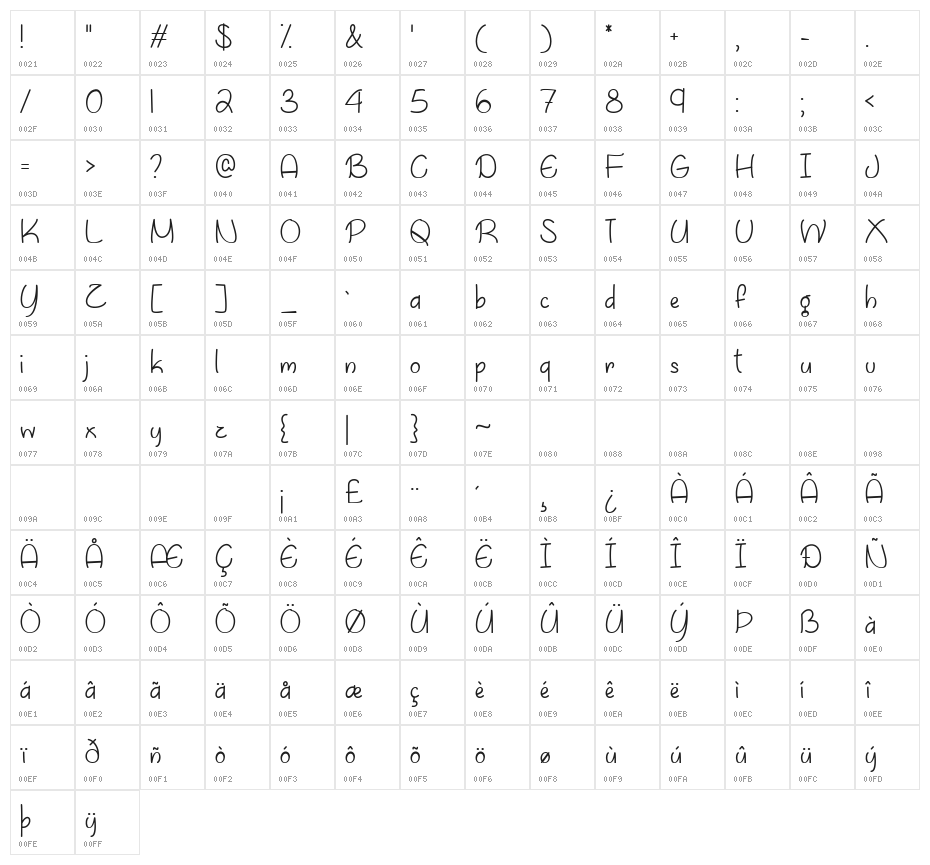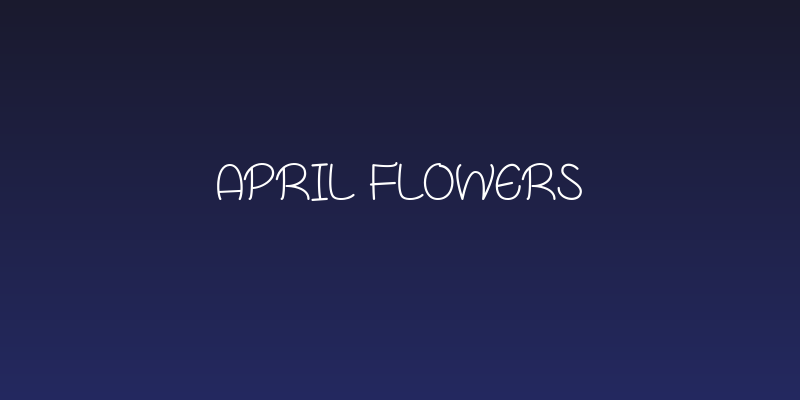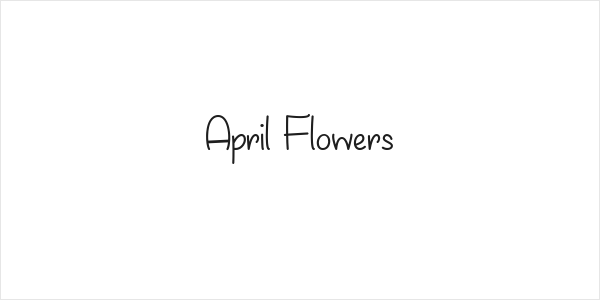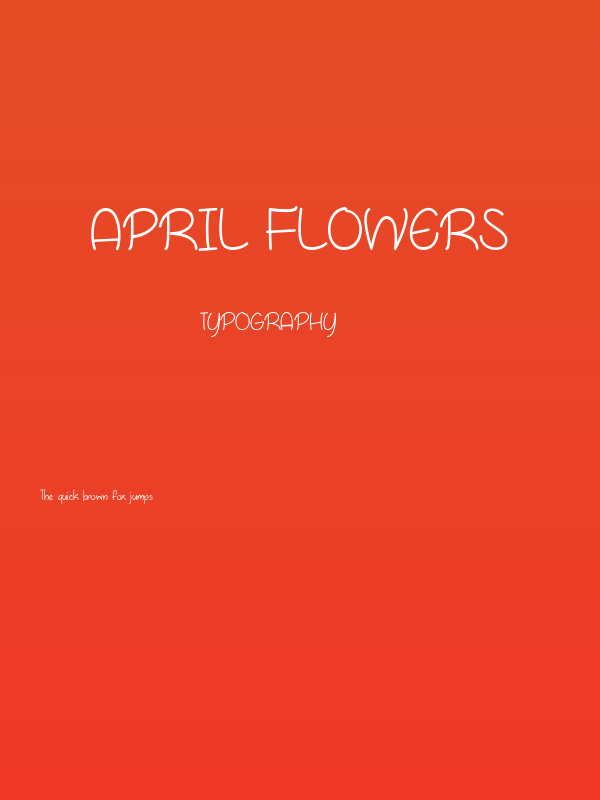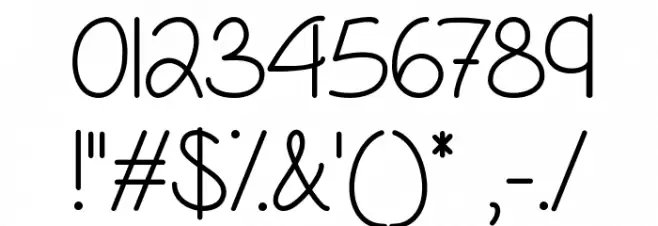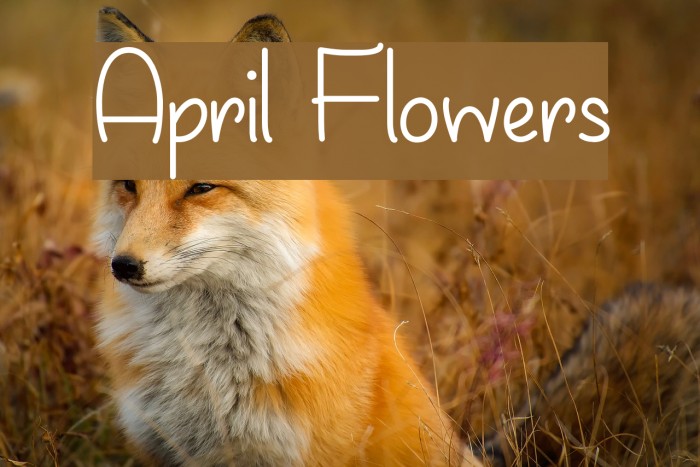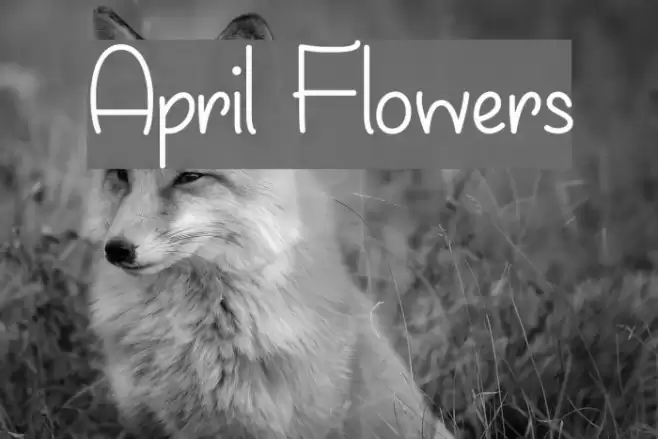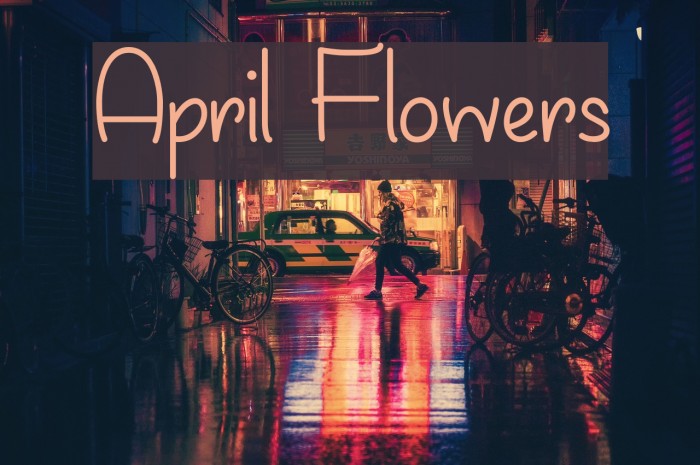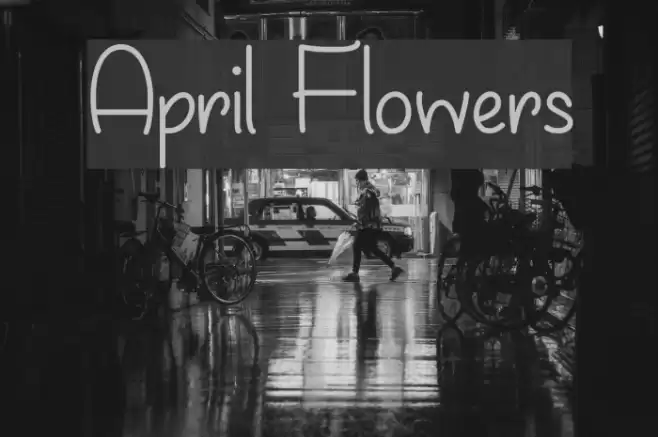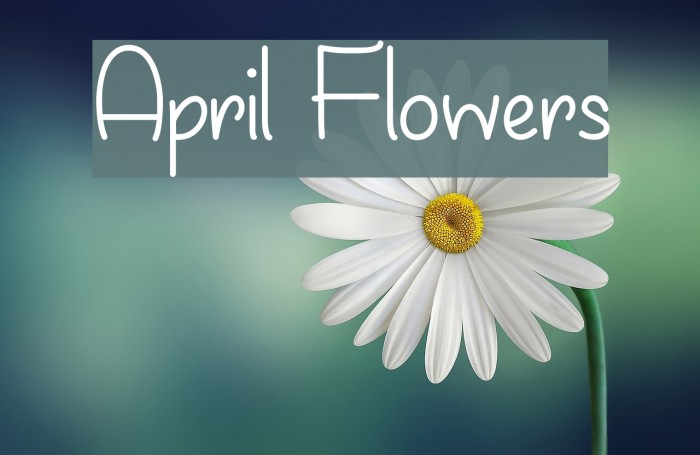
April Flowers Font
| 用途 | Headlines, Logos, Invitations |
| おすすめプロジェクト | Ideal for greeting cards, children's books, playful branding, and social media graphics. |